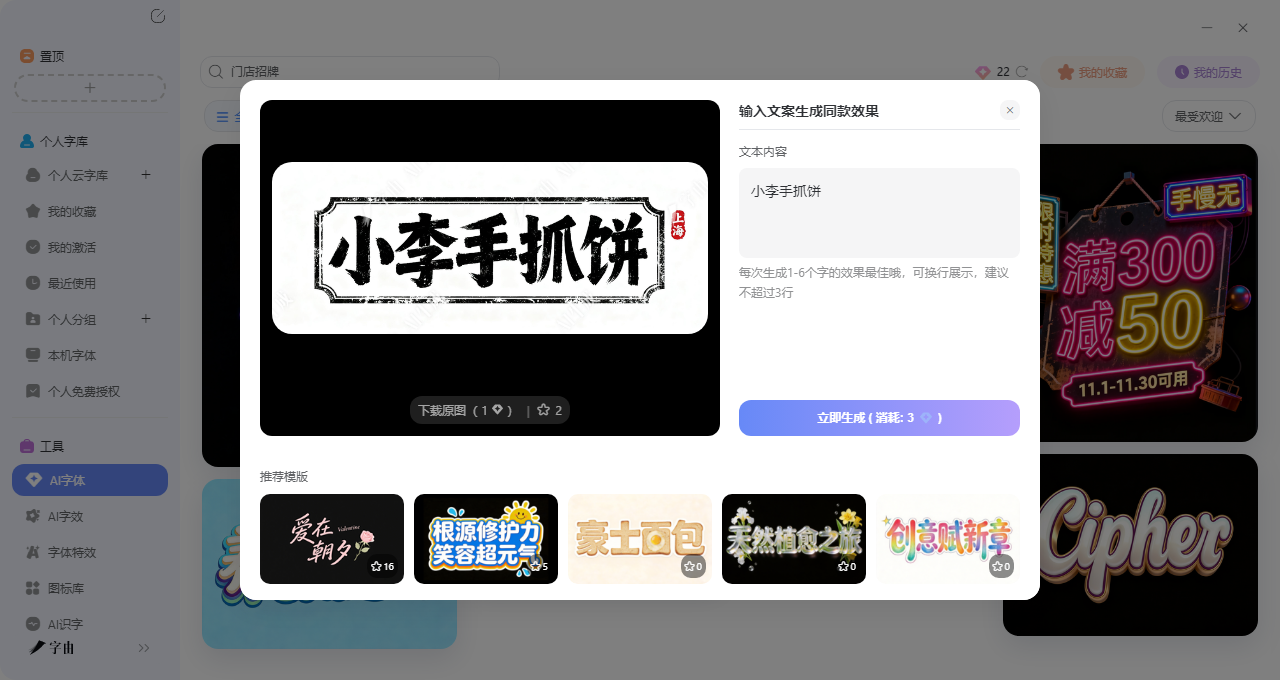
开新店愁招牌?这几个字体生成工具帮你省下设计费
开一家新的店面,从选址装修到进货备料,花钱的地方已经够多了。到了做招牌这一步,很多人开始犯难:请设计师设计个招牌字,少说几百上千;如果不涉及的话,招牌这种东西也会在某种程度上影响客流量,但是现在不用担心了,有不少门店招牌字体设计生成工具,能让你自己动手,花很少的钱甚至不花钱,就能做出像模像样的招牌字。今天我就筛选了4 个亲测好用的门店招牌字体设计生成工具,每个都能帮你快速搞定招牌字,需要的可以收藏!
你有没有想过,楼下那家生意火爆的“小李手抓饼”招牌,其实用字由就能做出来?字由有自带的AI工具就可以提供很多这样精致的模板,你只需要换掉文字内容,几十秒就能拿到一张自己的招牌字。你不用自己琢磨怎么做出霓虹灯管效果,也不用研究怎么把“XX火锅”四个字做出立体感。打开客户端,在AI字体里搜一下“门店招牌”,只需要十几秒就可以出一张直接用的招牌字,下面我会介绍详细的生成步:
第一步:进入AI字体页面后,在搜索框里输入“门店招牌”,系统会自动筛选出所有适合做招牌的模板。你也可以试试“招牌”“店招”“门头”这些词。
第二步:搜索结果会展示各种风格的预览图,每个模板都有独特的设计:
- 餐饮类:“重庆火锅”“小李手抓饼”这种,烟火气足,接地气
- 时尚类:“CLASSY”这种,简约高级,适合服装、美妆店
- 娱乐类:“舞厅”这种,复古霓虹,适合酒吧、Livehouse
- 促销类:“限时特惠”这种,冲击力强,适合活动招牌
每个模板都有预览图,如果拿不准,可以多试几个。
第三步:点击选中的模板,进入编辑页面。在输入框里填你想生成的店名,比如“张三烤串”“李四咖啡”“王五美发”。注意:最好和模板的字数保持一致,模板是四个字,你就填四个字;
第四步:确认文案后,点“立即生成”,等20-30秒左右就能拿到图。生成后可以预览效果,不满意就换其他模板再试,或者微调文案重新生成。每天有免费算力点,日常试用完全够用。
第五步:完成以后点击下载即可。
然后除了介绍步骤,我这里还会推荐一些好用的模板,方便你选择,在字由的AI字体里搜“门店招牌”,你会发现这些模板本身就很实用:
- “小李手抓饼”:这个模板是手写风格,字体活泼,带着一点烟火气。小吃摊、快餐店、夜市档口用这种字体,亲切感直接拉满。如果你想开个奶茶店或者炸鸡店,把文字换成店名,效果肯定不错。
- “重庆火锅”:这个模板是粗犷有力的字体,红红火火,一看就很有冲击力。火锅店、烧烤店、川菜馆用这种字体,顾客隔着马路都能感受到那股热辣劲儿。把文字换成“XX烧烤”“XX串串”,一样出效果。
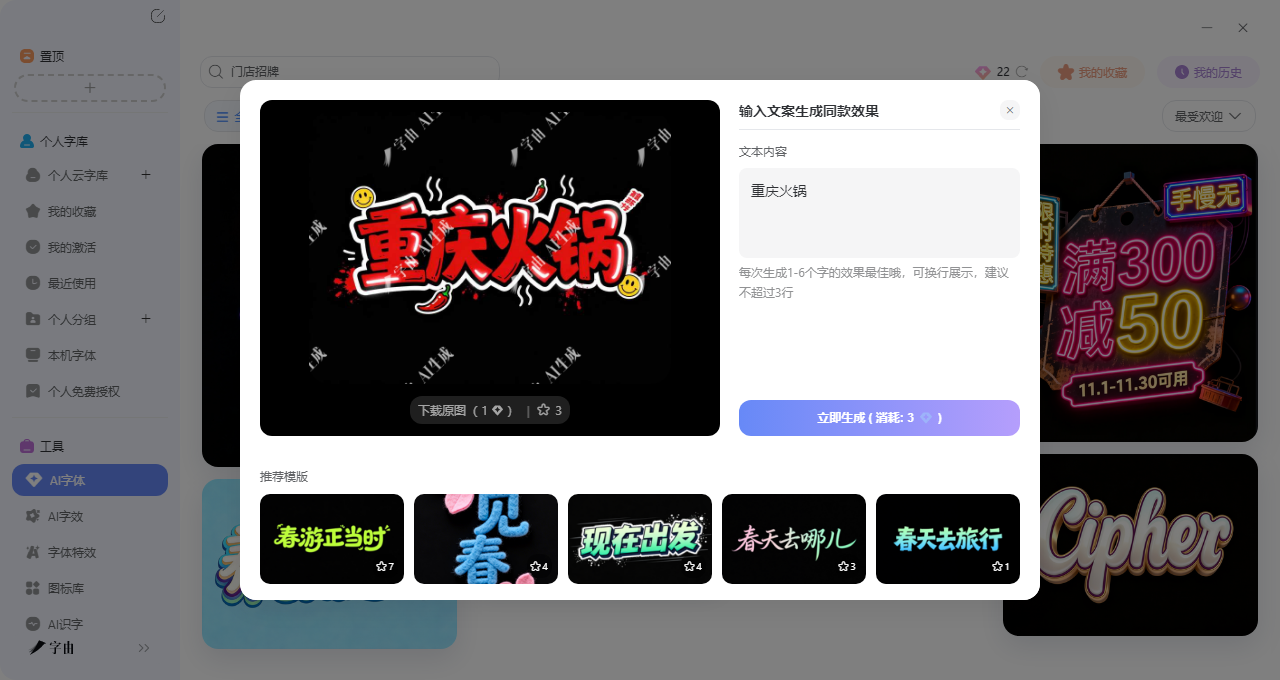
- “舞厅”:这个模板是复古霓虹风格,带着一点迪斯科年代的味道。适合清吧、Livehouse、夜店,或者任何想做复古风的店铺。霓虹灯的闪烁感,和夜晚的消费场景特别搭。
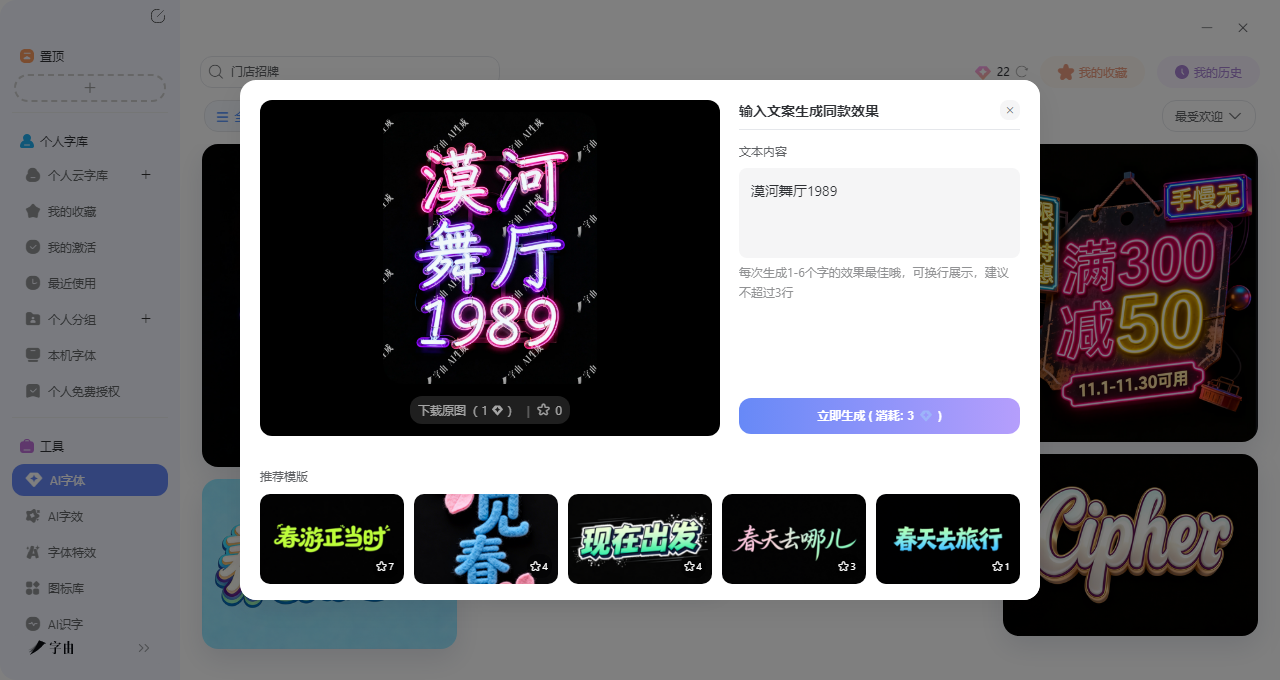
所以你看,字由的AI字体模板库远比我们想象的丰富。它不是只有“门店招牌”这个分类,你在“电商促销”“国潮风”里翻到的模板,稍微改一下文案和配色,都能变成你店里的招牌字。
2、Fontsc
Fontsc 是一个专门收集免费字体的网站,它有一个“Signage Fonts”分类,正好适合做门店招牌字体设计生成。从首页,这个分类下目前有75款字体,按热度排序,每款都标注了授权类型。
推荐几款值得关注的字体:
- Beon:由Bastien Sozoo设计,SIL OFL授权,<u>免费商用</u>。字体风格现代简洁,适合做服装店、咖啡店的招牌字。
- Las Enter:由Mäns Grebäck设计,免费个人或非商业使用。如果只是做个临时招牌,这款很合适。
网站还提供了热门标签(TRENDING FONT TAGS),比如“party”“luxury”“neon-lights”,这些标签可以帮助你快速找到适合店铺风格的字体。如果你需要做免费商用招牌字体的快速筛选,Fontsc是个不错的选择。
3、1001 Free Fonts
这里面几乎覆盖了所有门店可能用到的风格,但是实用程度可能不如字由了,但是好在这个网站每款字体都标注了授权类型,下载前记得看清楚。
4、The Color Archive
最后一个网站是The Color Archive,这是一个创意字体集市。虽然它不是专门的字体下载站,但这里的字体展示和推荐很有参考价值。这个网站适合用来找灵感,看看设计师们都在用什么风格的字体做招牌。